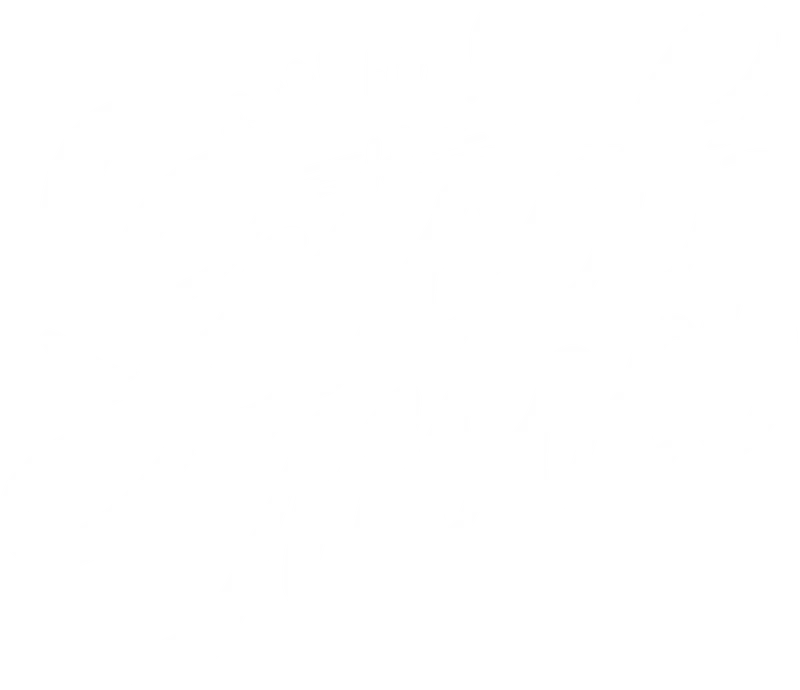
Câu nói "Good Food is Good Mood" font chữ đẹp
Câu nói "Good Food is Good Mood" font chữ đẹp — Thiết kế chữ "Good Food is Good Mood" độc đáo, truyền tải thông điệp tích cực về ẩm thực và tâm trạng. Phù hợp in chuyển nhiệt lên áo, túi, cốc.